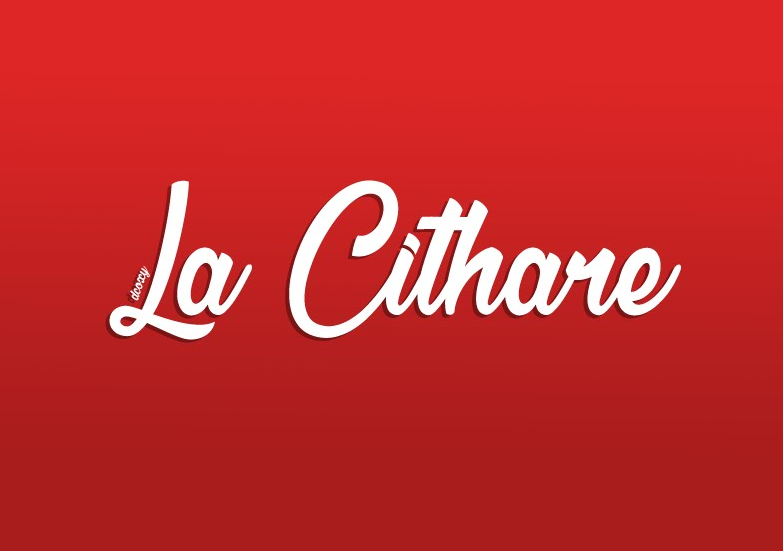
A La Cithare Font é uma deliciosa escolha para designers que buscam uma fonte typewriter com estilo único e natural para seus projetos pessoais. Ela foi criada pelo talentoso designer Hamilton, e oferece um ar vintage enquanto mantém sua versatilidade. Suas linhas leves e delicadas combina perfeitamente com textos clássicos e históricos, ou mesmo se adequa bem em criações mais modernas. Além disso, a La Cithare é uma fonte libre de uso pessoal apenas (sem promoção, logomarca, marca, thumbs, aplicativos, jogos, vídeos, papel, web, etc.), garantindo que você possa usá-la de forma privada sem preocupações legais. Aproveite a sua versão livre da La Cithare Font para criar designs autênticos e únicos, mantendo os princípios éticos do uso público em mente.